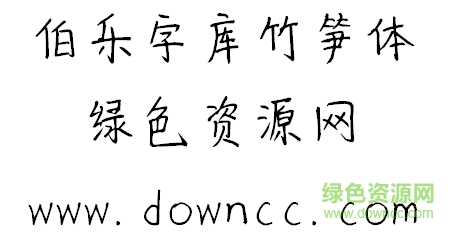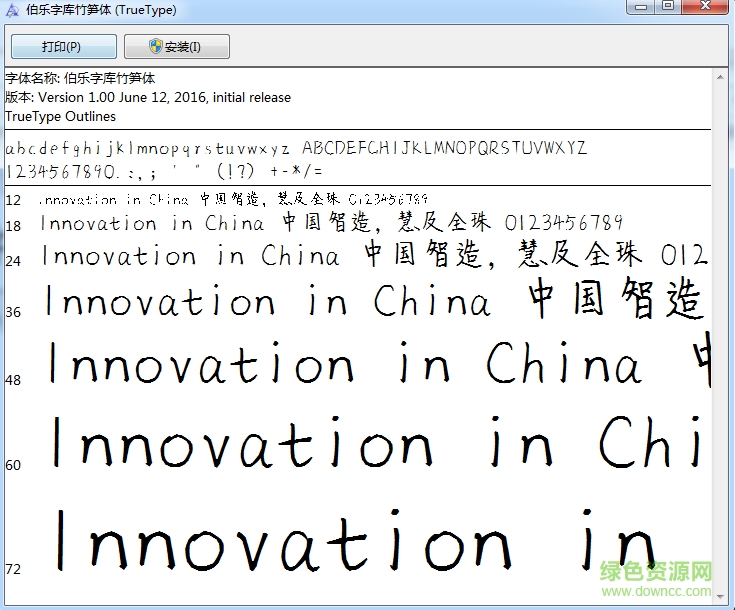
伯樂竹筍體是一款纖細(xì)娟秀的伯樂字體,延續(xù)了伯樂手寫體風(fēng)格,給人眼目一新的好感,讓你的字體更加獨(dú)特有個(gè)性,綠色資源網(wǎng)誠(chéng)意推薦!
伯樂竹筍體在伯樂系列字體中,很有自己獨(dú)特的魅力,字跡清晰很好辨認(rèn),造型簡(jiǎn)潔大方又不是靈動(dòng)活潑之感,筆觸連貫不拖沓,喜歡的朋友就來下載吧!